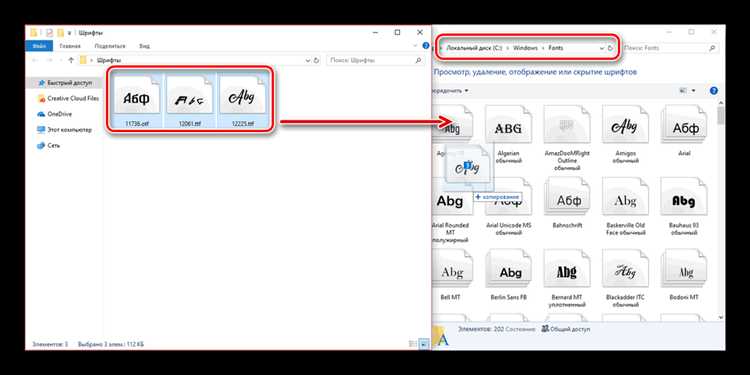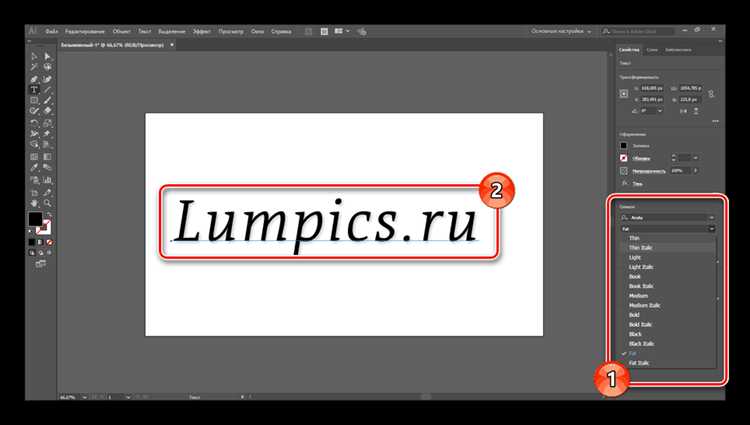
Adobe Illustrator поддерживает использование любых шрифтов, установленных в системе, однако процесс добавления нестандартных или недавно приобретённых шрифтов требует точного понимания работы с файлами шрифтов и их совместимости. Важно учитывать, что Illustrator распознаёт форматы OpenType (.otf), TrueType (.ttf) и PostScript Type 1, но для корректного отображения рекомендуется использовать именно OpenType.
Перед установкой необходимо проверить, чтобы шрифт не был защищён DRM и имел лицензию, позволяющую использовать его в коммерческих проектах. Установка новых шрифтов производится через системные средства операционной системы: в Windows – через Панель управления или приложение «Параметры», в macOS – через приложение «Каталог шрифтов» (Font Book). После установки Illustrator автоматически подгрузит новый шрифт при следующем запуске или после обновления списка шрифтов.
Для удобства работы с большими библиотеками шрифтов рекомендуются специальные менеджеры шрифтов, такие как Adobe Fonts (встроенный сервис Creative Cloud) или сторонние программы, например, NexusFont и FontBase. Они позволяют активировать и деактивировать шрифты без их постоянной установки в систему, что снижает нагрузку и ускоряет работу Illustrator.
В данной статье подробно рассмотрены шаги по установке новых шрифтов, рекомендации по проверке их корректного отображения в Adobe Illustrator и советы по решению распространённых проблем с загрузкой шрифтов.
Как выбрать и скачать шрифты для Adobe Illustrator
При выборе шрифтов для Adobe Illustrator обращайте внимание на совместимость форматов: оптимальны .OTF и .TTF. Эти форматы поддерживаются программой без дополнительной конвертации.
Для профессиональной работы выбирайте шрифты с полным набором кириллических символов, если вы работаете с русским текстом. Отсутствие поддержки кириллицы приведет к некорректному отображению.
Учитывайте назначение шрифта: для заголовков выбирайте выразительные, но читабельные гарнитуры с умеренной контрастностью. Для текста лучше подходят шрифты с высокой читаемостью при малых размерах – гарнитуры с равномерной толщиной и открытыми формами.
После скачивания рекомендуется проверить шрифт в специализированных программах для оценки качества и полноты символов, например FontForge или Glyphs, чтобы убедиться в корректности перед установкой в систему.
Установка шрифтов в операционной системе Windows и macOS
Для установки шрифтов в Windows достаточно открыть скачанный файл шрифта с расширением .ttf или .otf и нажать кнопку «Установить» в появившемся окне. Альтернативный способ – скопировать файлы шрифтов в папку C:\Windows\Fonts. После установки новые шрифты становятся доступны во всех приложениях, включая Adobe Illustrator, без необходимости перезагрузки системы.
В macOS для установки шрифтов используйте приложение «Каталог шрифтов» (Font Book). Запустите его через Spotlight, затем выберите меню «Файл» → «Добавить шрифты» и укажите путь к файлам с расширением .ttf или .otf. После добавления шрифты автоматически активируются и становятся доступными в Illustrator и других программах. Для установки шрифта только для текущего пользователя выберите «Добавить в коллекцию пользователя».
В обоих системах рекомендуется использовать шрифты из проверенных источников, чтобы избежать конфликтов и ошибок отображения. При массовой установке шрифтов лучше закрыть все программы, включая Illustrator, для корректного обновления списка шрифтов.
Как проверить доступность нового шрифта в Adobe Illustrator
После установки шрифта в систему откройте Adobe Illustrator и создайте новый документ или откройте существующий. Для проверки нового шрифта выберите инструмент «Текст» (горячая клавиша T) и кликните по рабочей области.
В панели свойств или в верхней панели управления найдите выпадающий список со шрифтами. Начните вводить название установленного шрифта, чтобы быстрее его найти. Если шрифт отображается в списке, он доступен для использования.
Если шрифт не появляется, перезапустите Illustrator. Иногда программа не обновляет список автоматически после установки новых шрифтов.
Для подтверждения корректности отображения шрифта введите несколько слов и измените их размер, чтобы проверить поддерживаемые начертания и стили.
В случае, если шрифт всё равно не виден, убедитесь, что он установлен корректно через системные средства управления шрифтами (например, «Каталог шрифтов» в macOS или «Панель управления» → «Шрифты» в Windows). Проверьте совместимость формата шрифта: Illustrator поддерживает TTF, OTF, а также некоторые форматы OpenType.
Можно ли временно добавить шрифт в Illustrator, не устанавливая его в систему?
В стандартной версии Adobe Illustrator такой возможности нет: программа использует системные шрифты. Однако можно использовать сторонние менеджеры шрифтов, которые загружают шрифты временно в систему, позволяя работать с ними без постоянной установки. После закрытия менеджера шрифт исчезает из списка программ.